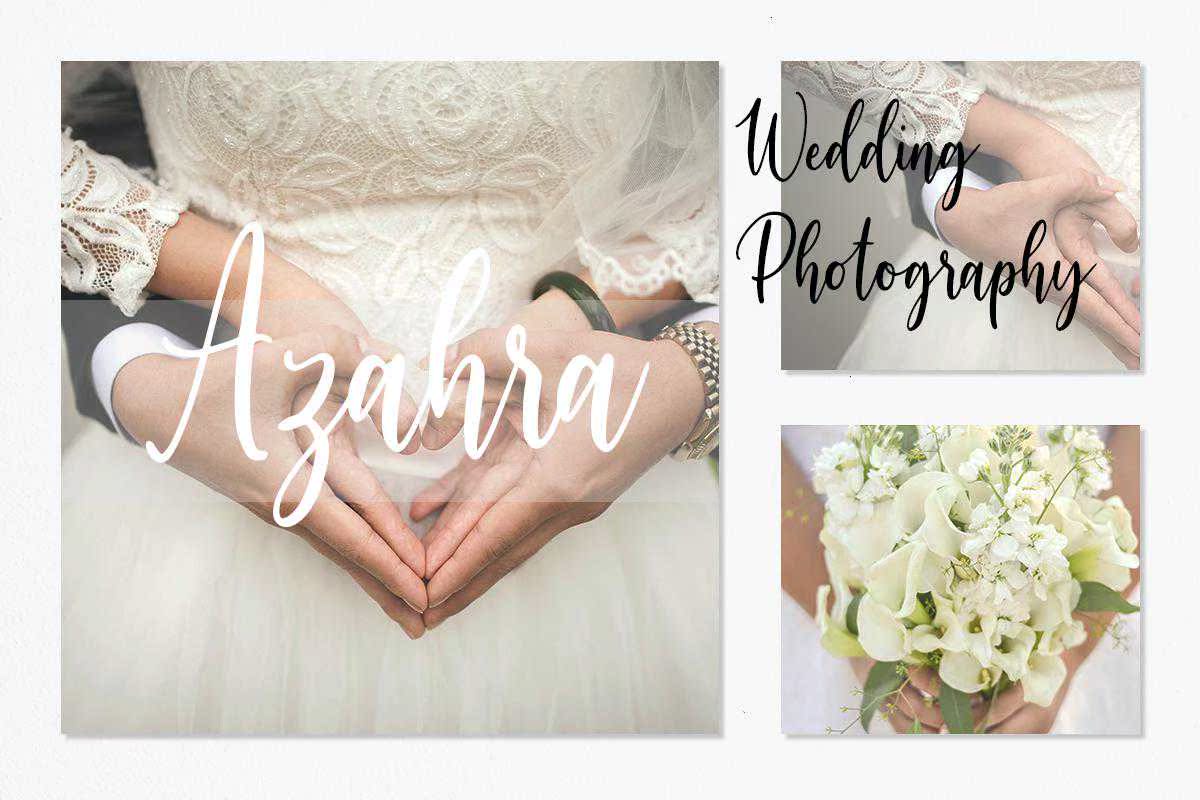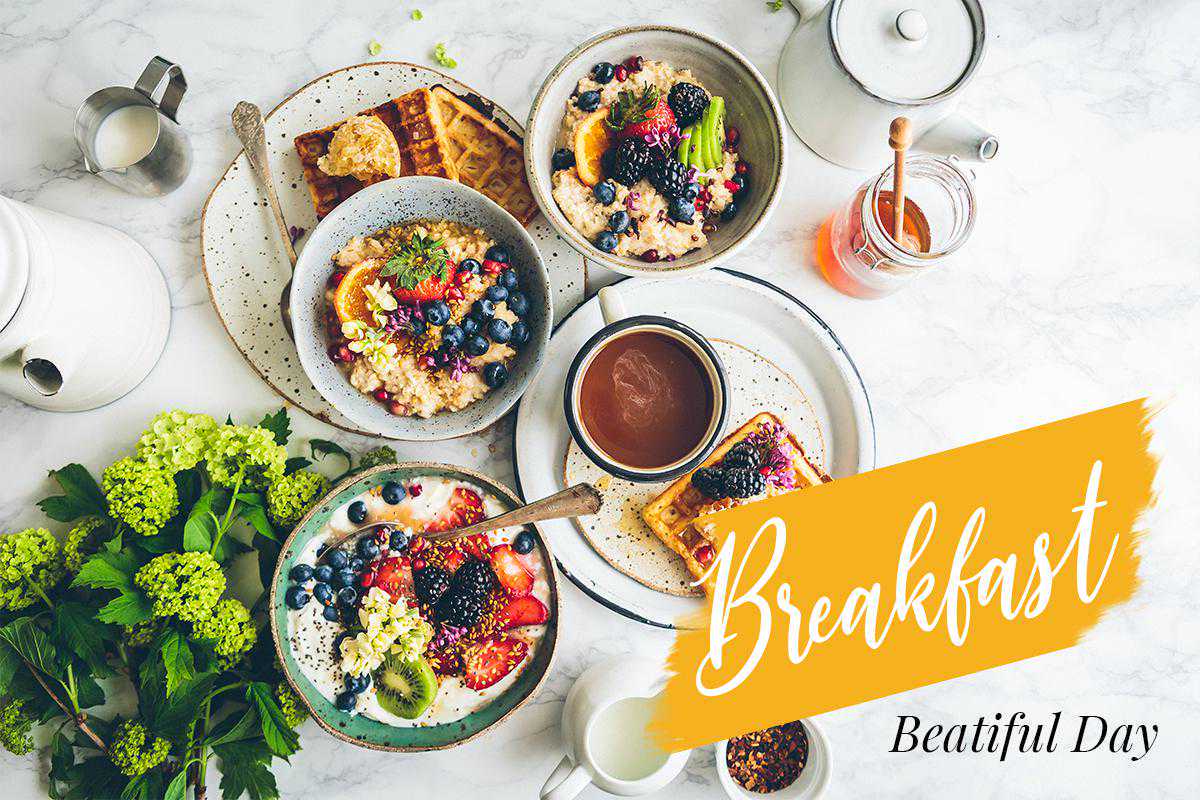
Manches将Eselegance简化为一个非常优秀的脚本字体。它将把广泛的设计项目提升到最高级别,包括品牌、标题、婚礼设计、邀请函、签名、徽标、标签等等!Manches将Eselegance简化为一个非常优秀的脚本字体。它将把广泛的设计项目提升到最高级别,包括品牌、标题、婚礼设计、邀请函、签名、徽标、标签等等!